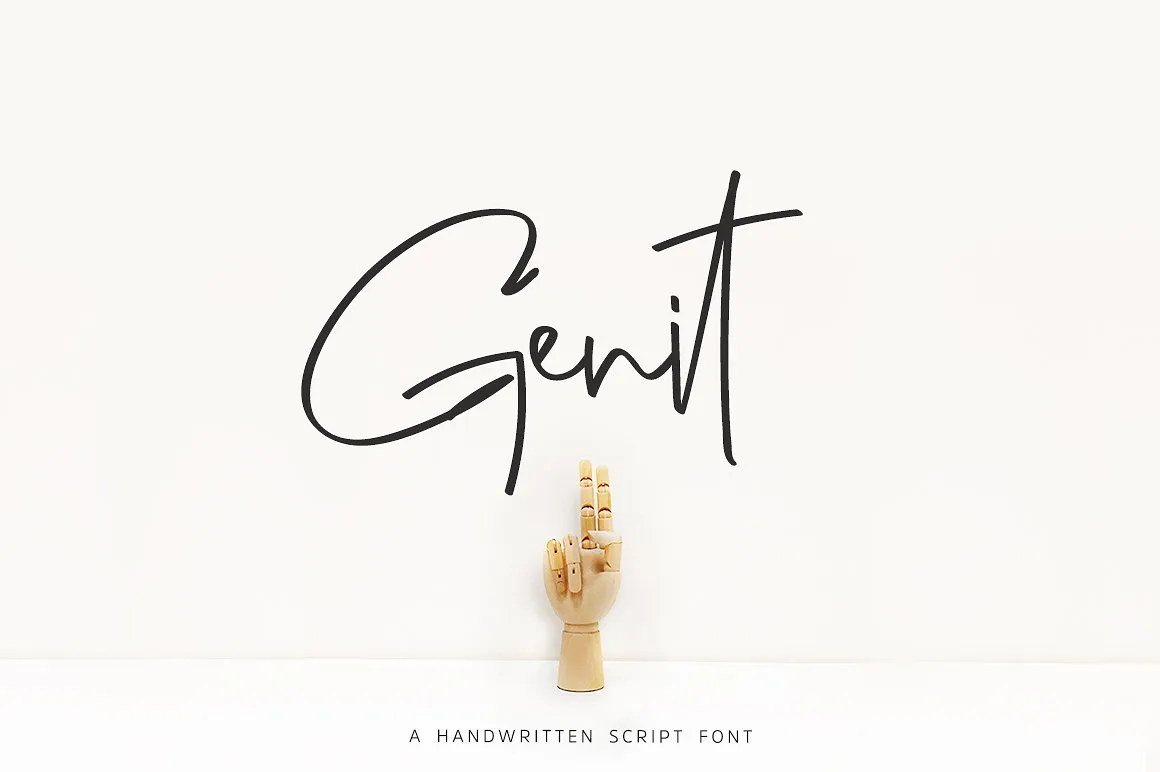
Genit Classy Handwritten Font – Download Grátis
A Genit Classy Handwritten Font é uma elegante escolha para projetos modernos que valorizam a sofisticação do handmade. Ela foi criada especialmente para designers que buscam uma fonte de script moderno com uma pitada de arte manual, adequada para tudo desde flyers e identidades corporativas até pacotes de produto e postagens nas redes sociais. Genit é perfeitamente adaptável a projetos minimalistas, proporcionando um toque refinado e natural. Suas linhas finas e elegantes fazem com que ela seja ideal tanto para personalizar logotipos quanto para criar texturas interessantes em suas criações digitais. Com sua natureza handmade embutida, essa fonte de script garante um resultado único e autêntico, dando vida à sua marca ou ideia através de detalhes cuidadosamente pensados que combinam a modernidade com o charme do artesanato. Ideal para quem deseja criar algo distinto e inovador em cada projeto. Seja você criando uma identidade visual completa ou apenas adicionando um toque único aos seus trabalhos, Genit é sua fonte perfeita para capturar o espírito contemporâneo com a personalidade autêntica que você deseja conferir à sua marca.